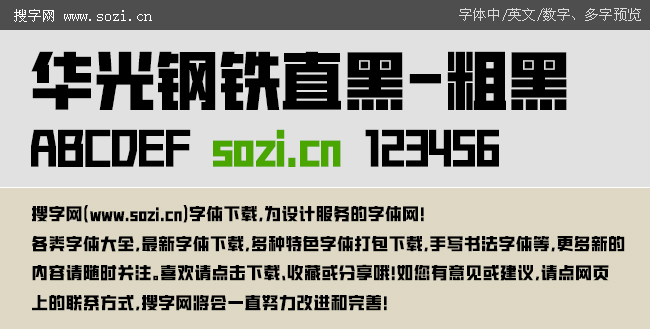
華光鋼鐵直黑-粗黑
搜字網(wǎng)給大家提供一款華光鋼鐵直黑-粗黑中文字體下載,華光鋼鐵直黑是一款藝術(shù)黑體字體。字體筆畫平直,線條規(guī)整,結(jié)構(gòu)扎實(shí),字形方正,視覺效果非常不錯 。免費(fèi)供大家使用。適合應(yīng)用于藝術(shù)設(shè)計(jì)、平面宣傳設(shè)計(jì)、網(wǎng)頁設(shè)計(jì)、海報(bào)設(shè)計(jì)等應(yīng)用。